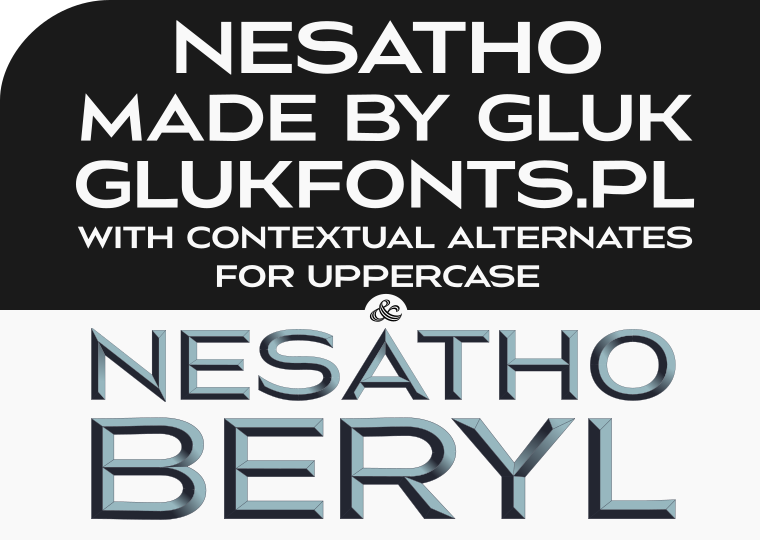
Sans font Nesatho z alternatywami kontekstowymi dla MINUSKUŁ, darmowy do użytku komercyjnego. Jako dodatek — wielokolorowy font OpenTypeSVG Nesatho-Beryl.